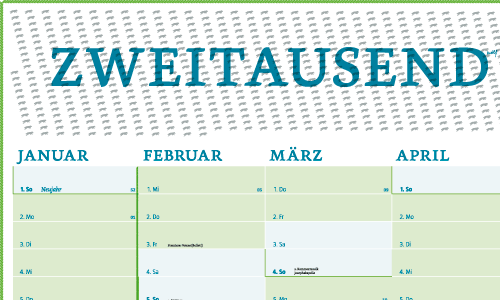
Simon, you made my day … ach was sag ich: my year. Mit diesem Wandkalender 2012 von Wehr und Weissweiler kann das Jahr nur gut werden. Kostenloses PDF laden und selbst drucken …
*Geschmacksache
Gefällt gut, aber es ist halt ein Wandplaner. Seit Jahren beschäftige ich mich schon mit Kalender-Layouts und musste lernen: Wenn das Ding wirklich gut benutzbar sein soll, dann erhält man im Ergebnis zwangsläufig immer so einen Speditions-Druckerei-Schnurrbart-Wandplaner-Look, weil die 52 Wochen nun mal so sperrig sind wie sie sind, trotz guter Typo, netten Farben usw. Wir haben es vor Jahren mal erfolgreich mit Dreidimensionalität versucht (http://kraftpapier.com/kraftpapier-studioplaner.jpg) aber so ein Kalender wird in der Herstellung arg teuer. Bei kleinen Terminplanern kann man mit Gestaltung und wenig Aufwand einiges gutes bewirken, aber dank Smartphones ist das ja bald kein Markt mehr.
Diese Übersicht ist von einem Smartphone nie zu erreichen: Size does matter.
Analog rules!
sorry, auch wenn hier alles gehypt wird was von wehr & weissweiler kommt — ich find das teil hässlich und langweilig, außerdem ist mir das worauf es bei einem kalender ankommt, nämlich die zahlen und die tage viel zu klein, die operneinträge interessieren mich auch reichlich wenig. aber einem geschenkten gaul schaut man ja nicht ins maul, frage mich allerdings auch wieso man sich heute noch die wand mit kalendern vollhängen soll — in zeiten synchronisierter kalender.
Welche Schrift wurde denn für den Kalender verwendet? Insbesondere für die Headline sowie die Monate. Wäre toll, wenn das jemand wüsste.
überschrift und ‘kleingedrucktes’ dürfte dolly von underware sein.